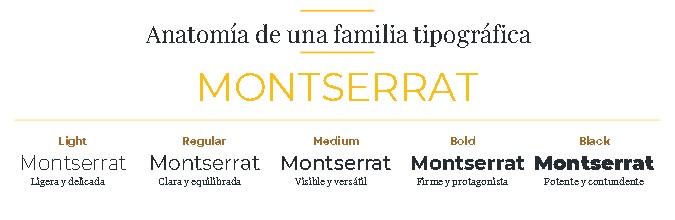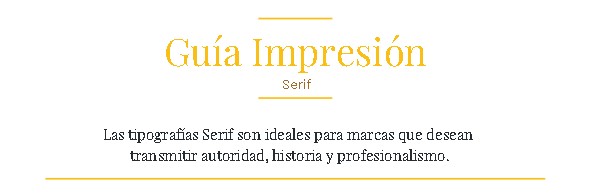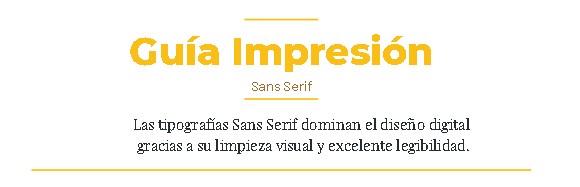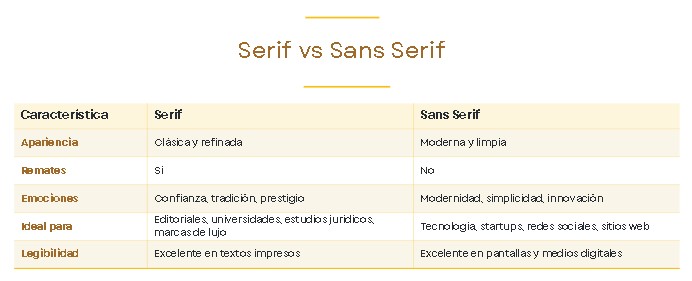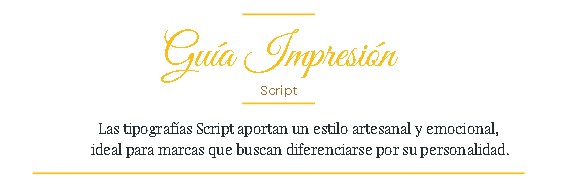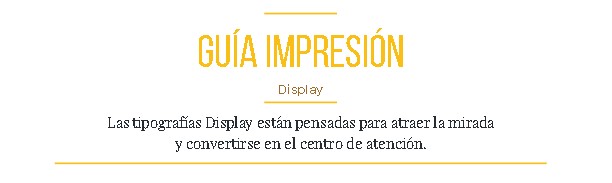
¿Alguna vez te preguntaste por qué una misma palabra puede parecer elegante, moderna, seria o divertida sin cambiar una sola letra?
La respuesta está en la tipografía.
Antes de que una persona lea un mensaje, su cerebro ya comenzó a interpretar la forma de las letras. Esa primera impresión puede transmitir confianza, innovación, cercanía, exclusividad o incluso generar rechazo. Por eso, la elección de una tipografía nunca debería ser una decisión tomada únicamente por cuestiones estéticas.
Cada fuente posee una personalidad propia. Sus formas, proporciones, grosor, remates y curvas despiertan asociaciones que influyen en la manera en que percibimos una marca, un producto o un anuncio. En otras palabras, las tipografías también comunican.
En el diseño gráfico, la identidad visual de una empresa no depende solamente del logotipo o de los colores corporativos. La tipografía forma parte de ese lenguaje visual y tiene la capacidad de reforzar los valores de una marca, mejorar la legibilidad de un mensaje y generar una conexión emocional con el público.
En esta guía descubrirás qué es la psicología tipográfica, cuáles son las principales familias de fuentes, qué emociones transmite cada una y cómo las grandes marcas utilizan las tipografías para construir una identidad visual sólida.
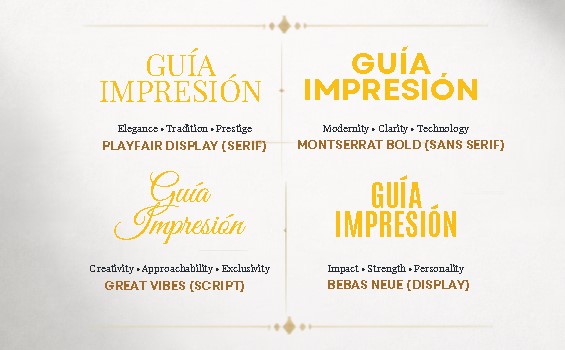
La tipografía cambia la percepción del mensaje, incluso cuando las palabras son exactamente las mismas.
A simple vista puede parecer un detalle menor, pero basta con observar la misma frase escrita con distintas tipografías para comprobar cómo cambia la sensación que transmite. Nuestro cerebro no interpreta únicamente las palabras: también analiza la forma en que están escritas. Esa reacción ocurre en apenas unos segundos y condiciona la manera en que percibimos una marca o un mensaje.
¿Qué es la psicología tipográfica?
La psicología tipográfica estudia cómo las formas de las letras influyen en la percepción y en las emociones de las personas. Aunque muchas veces no somos conscientes de ello, estamos expuestos constantemente a tipografías: en carteles, envases, páginas web, redes sociales, revistas, anuncios y logotipos.
Cada tipografía posee una personalidad propia. Algunas pueden parecernos elegantes y refinadas; otras, modernas y simples; mientras que ciertas fuentes transmiten cercanía, creatividad, fuerza o informalidad.
Estas sensaciones no dependen únicamente de las palabras que leemos. También están relacionadas con la forma de los caracteres, el grosor de los trazos, la presencia o ausencia de remates, las curvas, el espacio entre letras y las proporciones de cada diseño tipográfico.
La psicología tipográfica analiza precisamente esa relación entre la apariencia de las letras y las emociones o asociaciones que despiertan en quien las observa.
Por esta razón, la elección de una fuente debe acompañar el propósito del mensaje. Si una tipografía no coincide con el contenido o con la personalidad de la marca, puede generar una desconexión visual y confundir al público.
Por ejemplo, una empresa que desea transmitir seriedad y trayectoria probablemente no produzca la misma impresión si utiliza una tipografía infantil o excesivamente decorativa. Del mismo modo, una marca joven y tecnológica podría parecer antigua si recurre a una fuente demasiado clásica y formal.
La clave está en lograr coherencia entre lo que se dice y la manera en que ese mensaje se presenta visualmente.
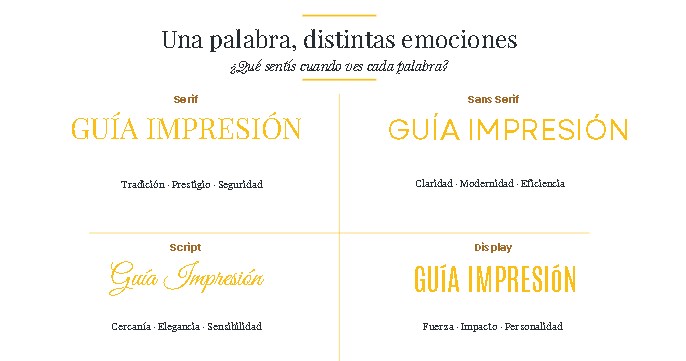
La palabra es la misma, pero la sensación cambia según la tipografía.
El ejercicio demuestra que no interpretamos una palabra únicamente por su significado. La forma en que está escrita también modifica su personalidad. Una fuente puede reforzar el mensaje, suavizarlo, volverlo más serio o hacerlo mucho más llamativo.
Por eso, antes de elegir una tipografía conviene preguntarse:
¿Qué emoción quiero generar?
¿Qué personalidad debe transmitir la marca?
¿La forma de las letras acompaña realmente el contenido?
Tipografía, fuente y familia tipográfica: ¿son lo mismo?
Aunque suelen utilizarse como sinónimos, los términos tipografía, fuente y familia tipográfica no significan exactamente lo mismo.
Conocer la diferencia ayuda a trabajar de manera más precisa y a organizar correctamente un sistema visual.
¿Qué es una tipografía?
La tipografía es el diseño general de un conjunto de caracteres. Incluye letras, números, signos de puntuación y símbolos que comparten una misma identidad visual.
Algunos ejemplos conocidos son:
- Helvetica
- Garamond
- Futura
- Montserrat
- Times New Roman
Cuando hablamos de Montserrat, por ejemplo, nos referimos al diseño tipográfico completo y a las características visuales que distinguen a sus letras.
¿Qué es una fuente?
Una fuente es una versión específica dentro de una tipografía.
Puede variar según:
- el grosor;
- la inclinación;
- el ancho;
- el estilo;
- el peso visual.
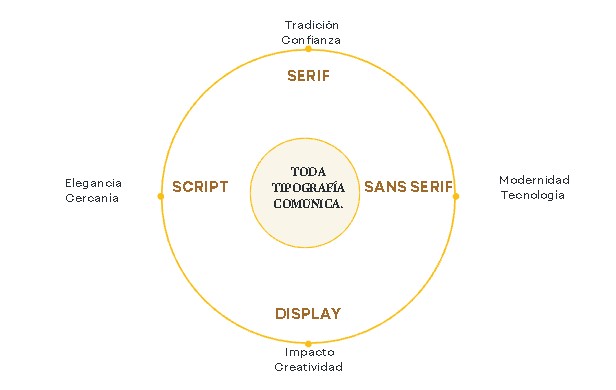
No existe una tipografía mejor que otra. Existe una tipografía más adecuada para cada mensaje.
Elegir una tipografía no significa seguir una moda, sino encontrar aquella que mejor represente la personalidad de una marca y acompañe el mensaje que se desea transmitir.
Una misma palabra puede inspirar confianza, parecer innovadora, resultar elegante o captar la atención únicamente cambiando la forma de sus letras. Comprender estas diferencias permite diseñar con mayor intención y lograr una comunicación mucho más efectiva.